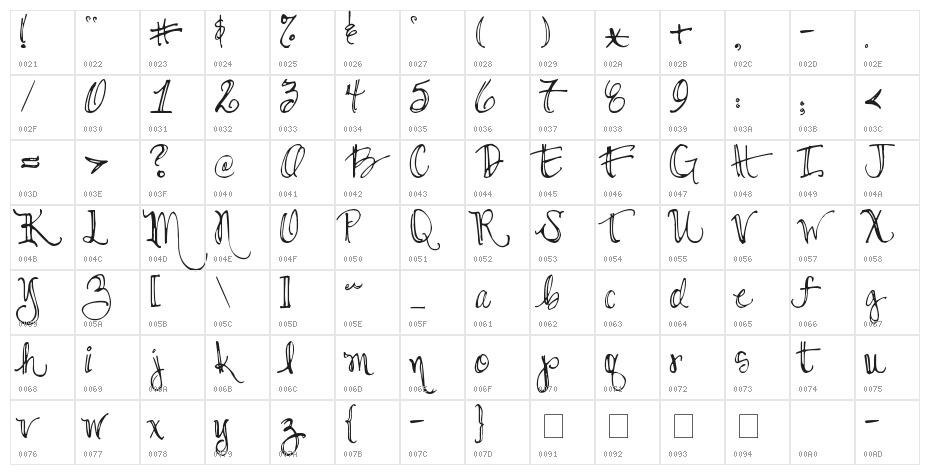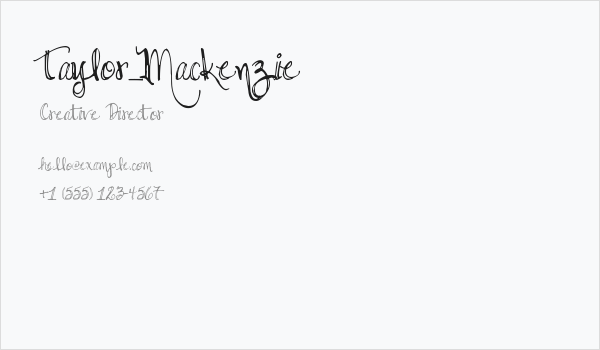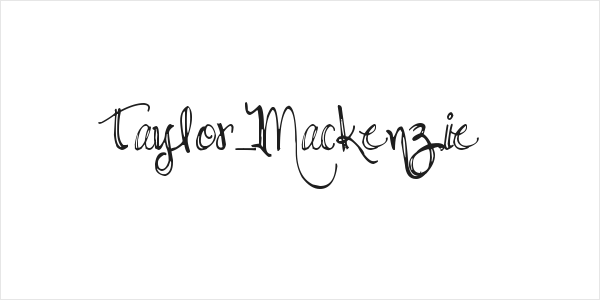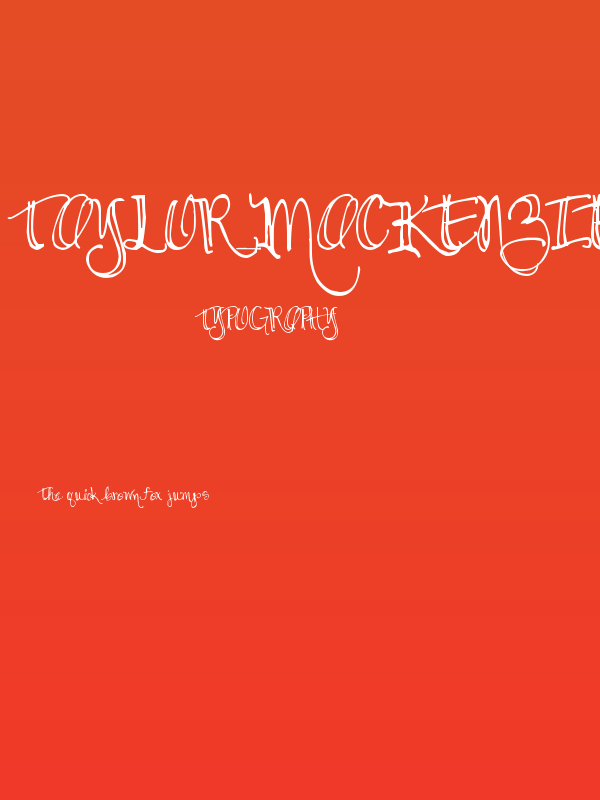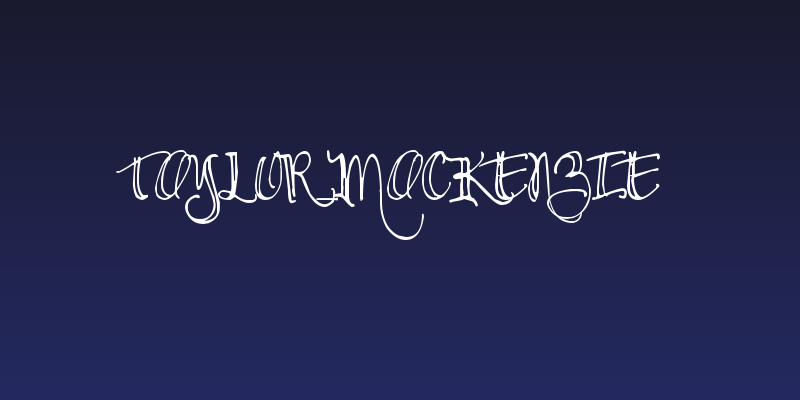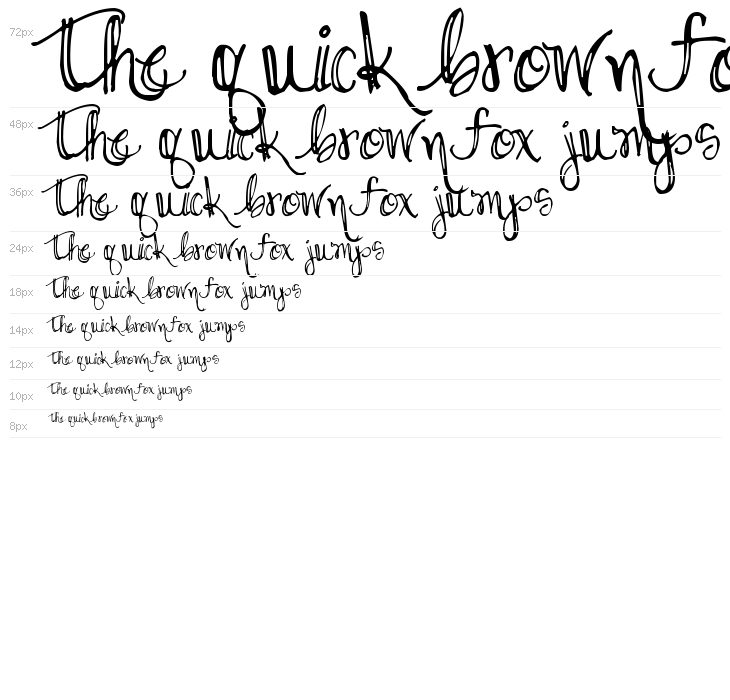
Taylor_Mackenzie Font
TAYLOR_MACKENZIE MAIUSCOLE
TAYLOR_MACKENZIE MINUSCOLO
TAYLOR_MACKENZIE ALTRI CARATTERI
| Caso d'uso | Logos, Headlines, Artistic projects |
| Progetti proposti | Ideal for invitations, greeting cards, artistic posters, and branding materials that require a personal and creative touch. |